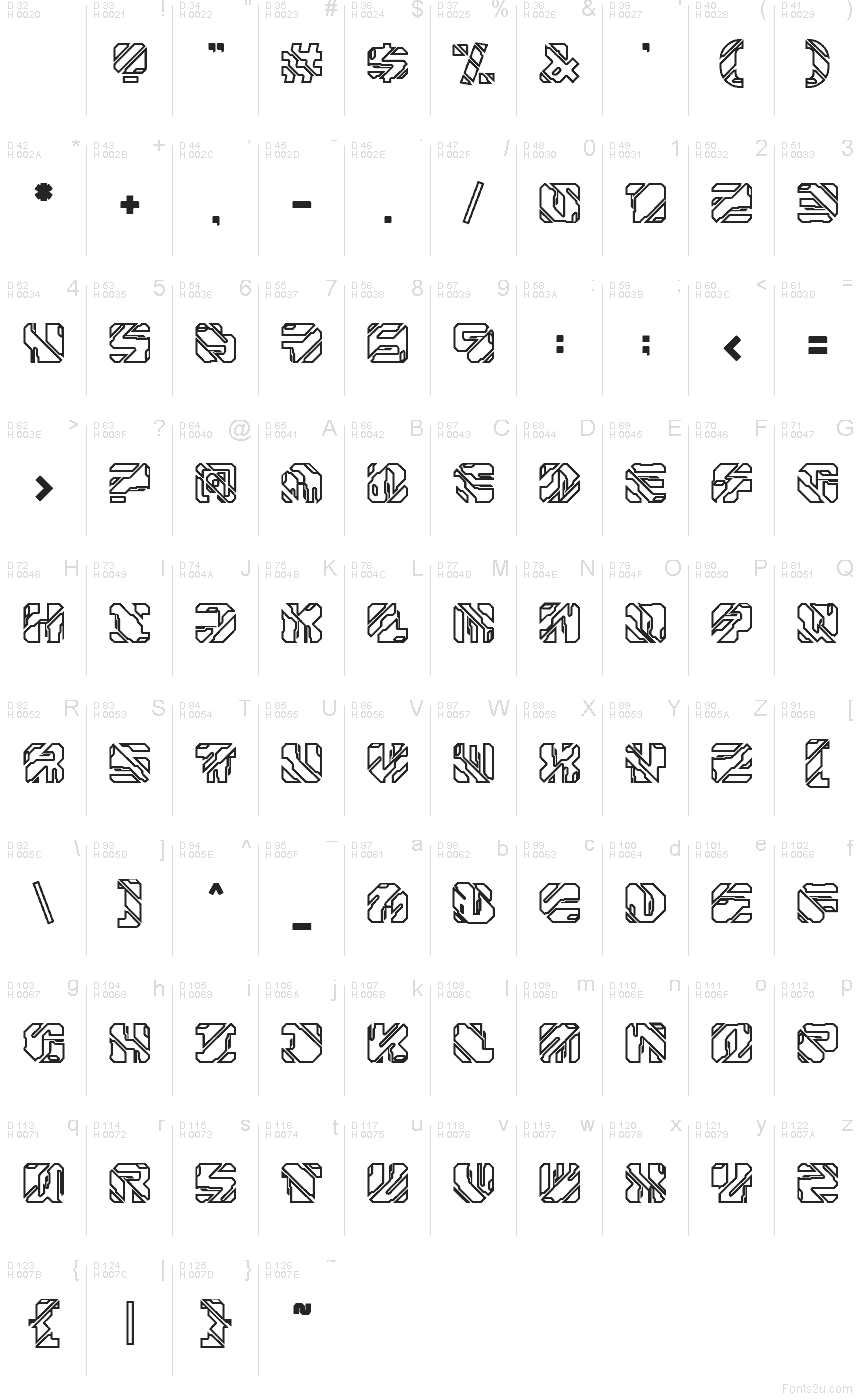
Space Sparkle Five od Putracetol Studio je bezplatné futuristické displejové písmo, které je tvarováno jako síť hranatých panelů a vyfrézovaných drah. Jeho opakující se zkosené rohy, vyřezávané sekce a rovnoběžné vnitřní linie dodávají písmenům technický, kompartmentovaný rytmus, který působí spíše jako grafika sci-fi rozhraní než jako běžné techno písmo.
Tato konstrukce se skvěle hodí pro názvy her, e-sportovní branding, titulky plakátů, obaly hudebních alb a streamovací grafiku, kde segmentované tvary samy o sobě nesou digitální téma. Dokáže také dodat ostrý a schematický vzhled obalům nebo identitám akcí spojených s vesmírem, robotikou či elektronickou kulturou, zejména pokud potřebujete, aby krátká slova působila tvrdě a technicky.